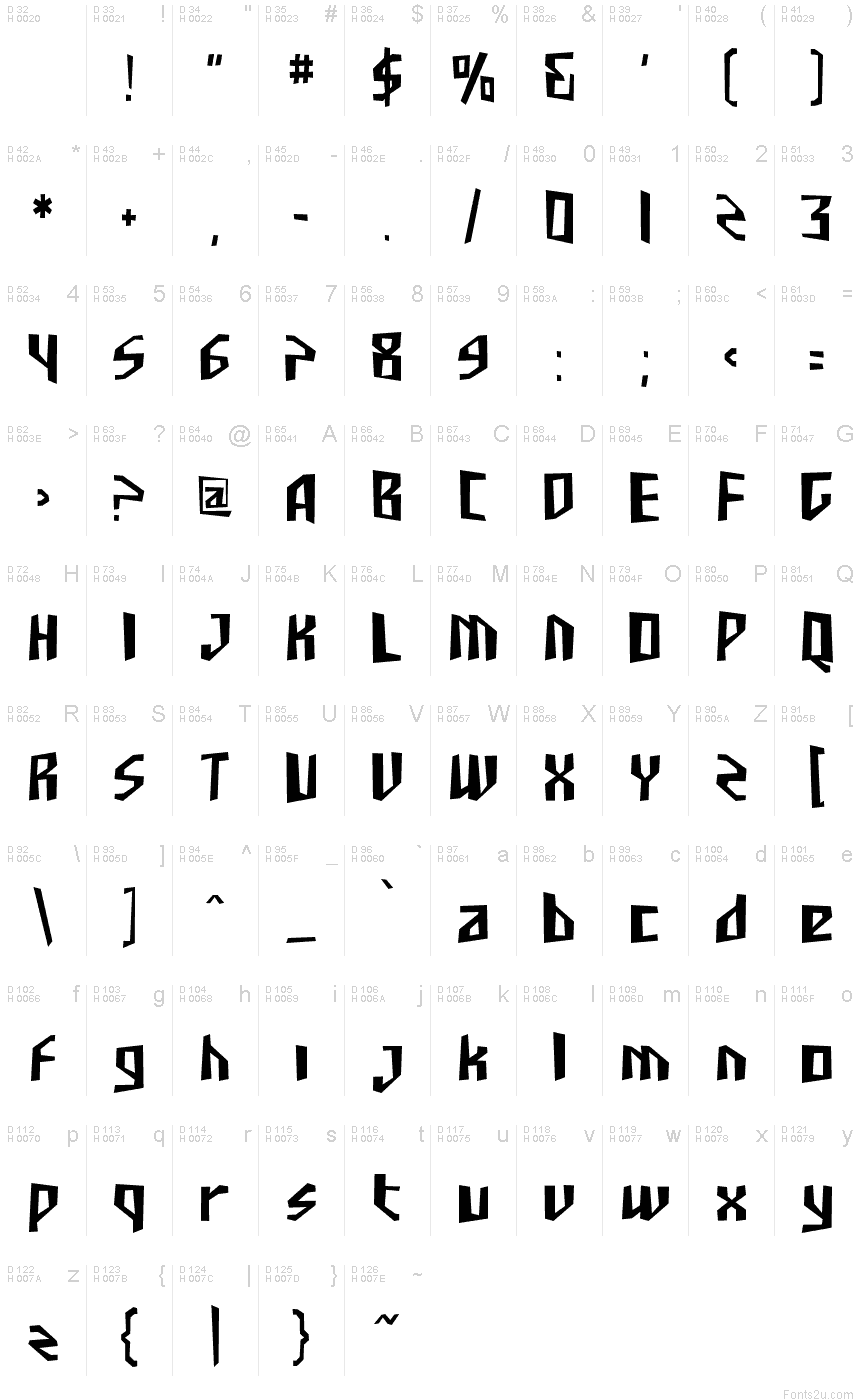
Podgląd czcionki SF Junk Culture Condensed
SF Junk Culture Condensed od ShyFonts Type Foundry to darmowy font display w komiksowym stylu, inspirowany wycinankami z papieru, o zadziornym, ręcznie robionym charakterze. Wielkie litery wyglądają, jakby zostały wycięte z czarnego kartonu i lekko przesunięte; mają ostre rogi, nierówne kąty i niespokojny rytm, który bardziej kojarzy się z zinami i kolażami niż z wygładzonymi kreskówkami.
Sprawdzi się na plakatach, okładkach mixtape'ów, ulotkach skejtowych, w nagłówkach komiksów niezależnych i planszach tytułowych, gdzie darmowy font ma nieść głośny, improwizowany przekaz bez potrzeby długich tekstów. Użyj go w krótkich nagłówkach, hasłach na okładkach czy monogramach, gdy chcesz, aby litery wyglądały na składane ręcznie – bo ten poszarpany, "sklejony" wygląd to w tym przypadku cały zamysł.
Prezentacja i próbka wizualna czcionki SF Junk Culture Condensed
Mapa znaków czcionki SF Junk Culture Condensed
Mapa znaków czcionki SF Junk Culture Condensed: Podstawowy łaciński, strona 1
Glify czcionki SF Junk Culture Condensed — Podstawowy łaciński, strona 1